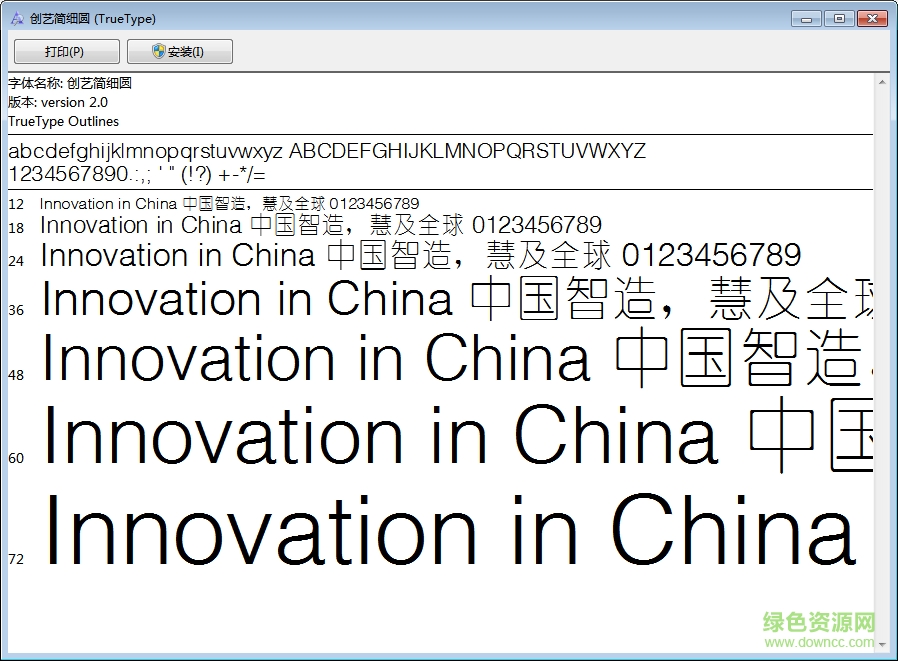
創(chuàng)藝簡(jiǎn)細(xì)圓字體是一款非常優(yōu)雅的創(chuàng)藝字體,筆畫非常的細(xì)膩,一筆一劃非常的清晰,有一種細(xì)長(zhǎng)的效果,非常的簡(jiǎn)潔大方,歡迎喜愛此字體的朋友到綠色資源網(wǎng)下載使用!
創(chuàng)藝簡(jiǎn)細(xì)圓字體是一款用于藝術(shù)設(shè)計(jì)方面的字體,創(chuàng)藝簡(jiǎn)細(xì)圓字體筆畫均衡,折角處圓潤(rùn)沒有棱角。